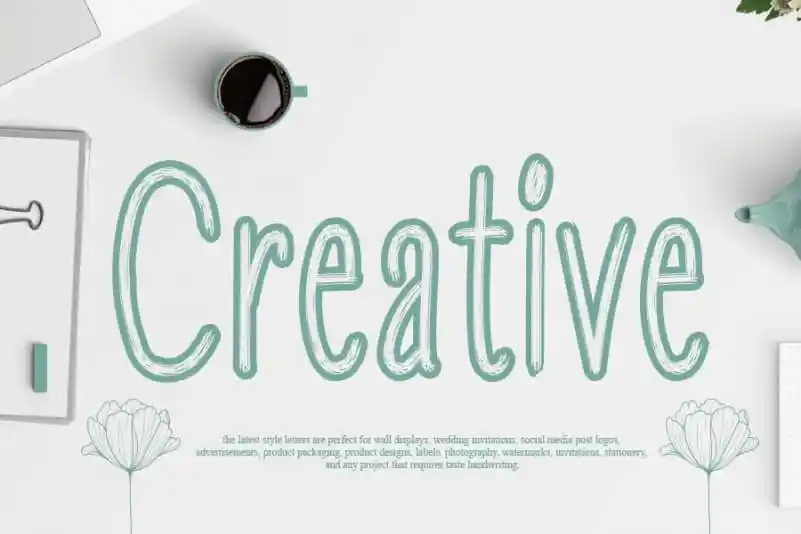
Creative Script Font – Download Grátis
Creative Script Font é uma fonte escrita a mão leve, que traz consigo um toque descontraído e divertido à sua identidade visual. Suave, mas com um toque de personalidade, essa fonte idealmente combina com seus logotipos, marcas, projetos de mídias sociais e até mesmo os seus DIYs criativos. É uma escolha perfeita para quem valoriza tanto a elegância quanto o charme peculiar, oferecendo um toque único que torna qualquer projeto destaco. Com Creative Script Font, transforme sua marca em algo ainda mais especial.